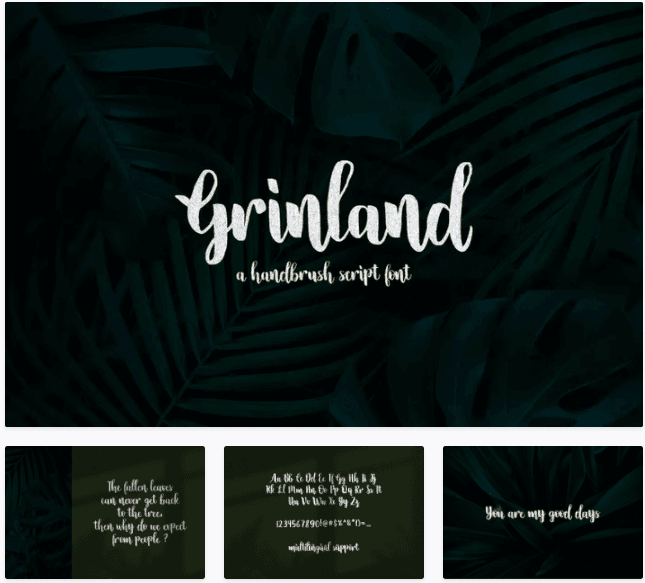
Grinland font
Grinland - это шрифт ручной кисти, вдохновленный современной каллиграфией. Гринланд имеют очень грубый характер и органические. Подходит для природы или нарисованного вручную дизайна тема.